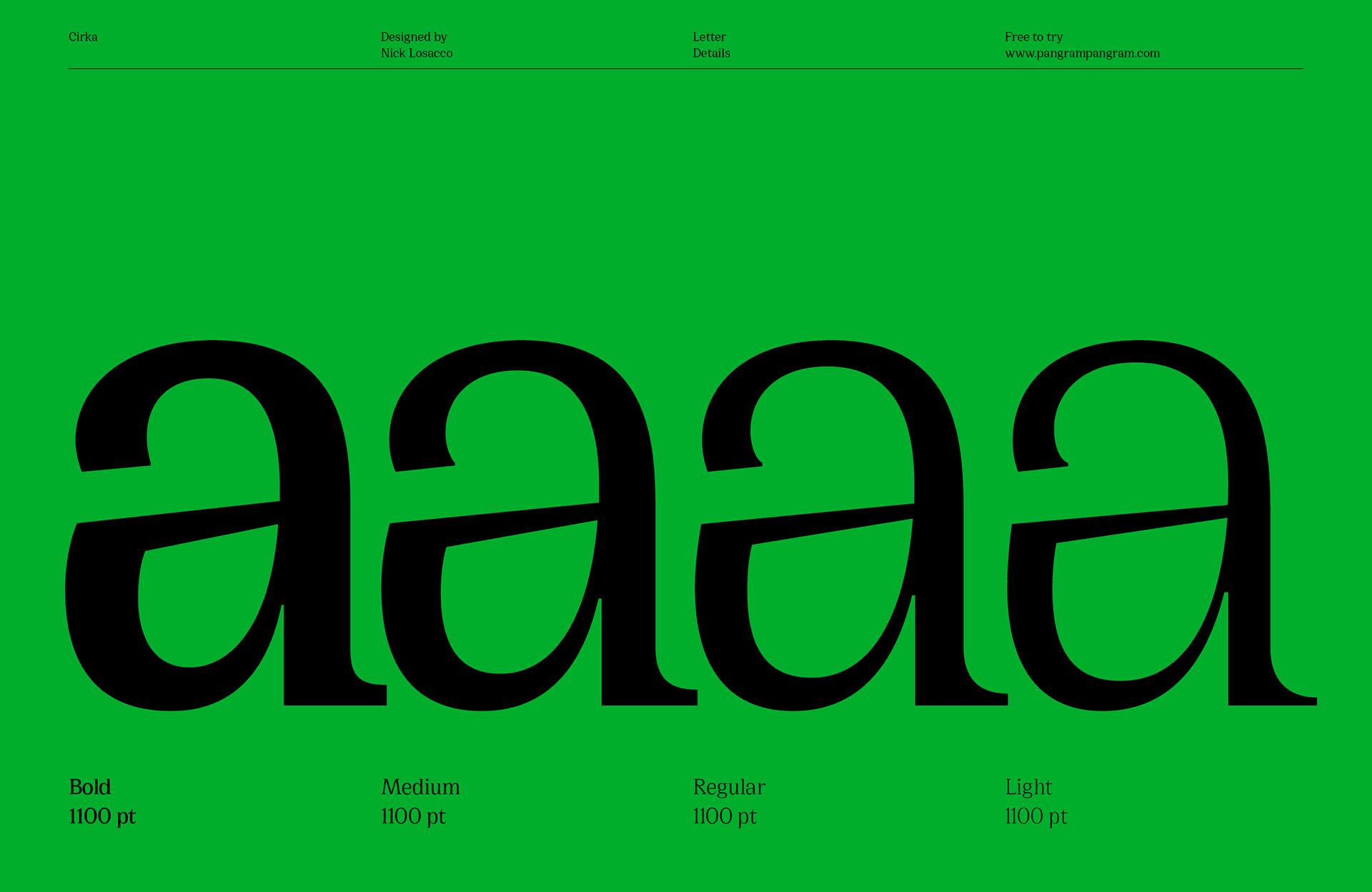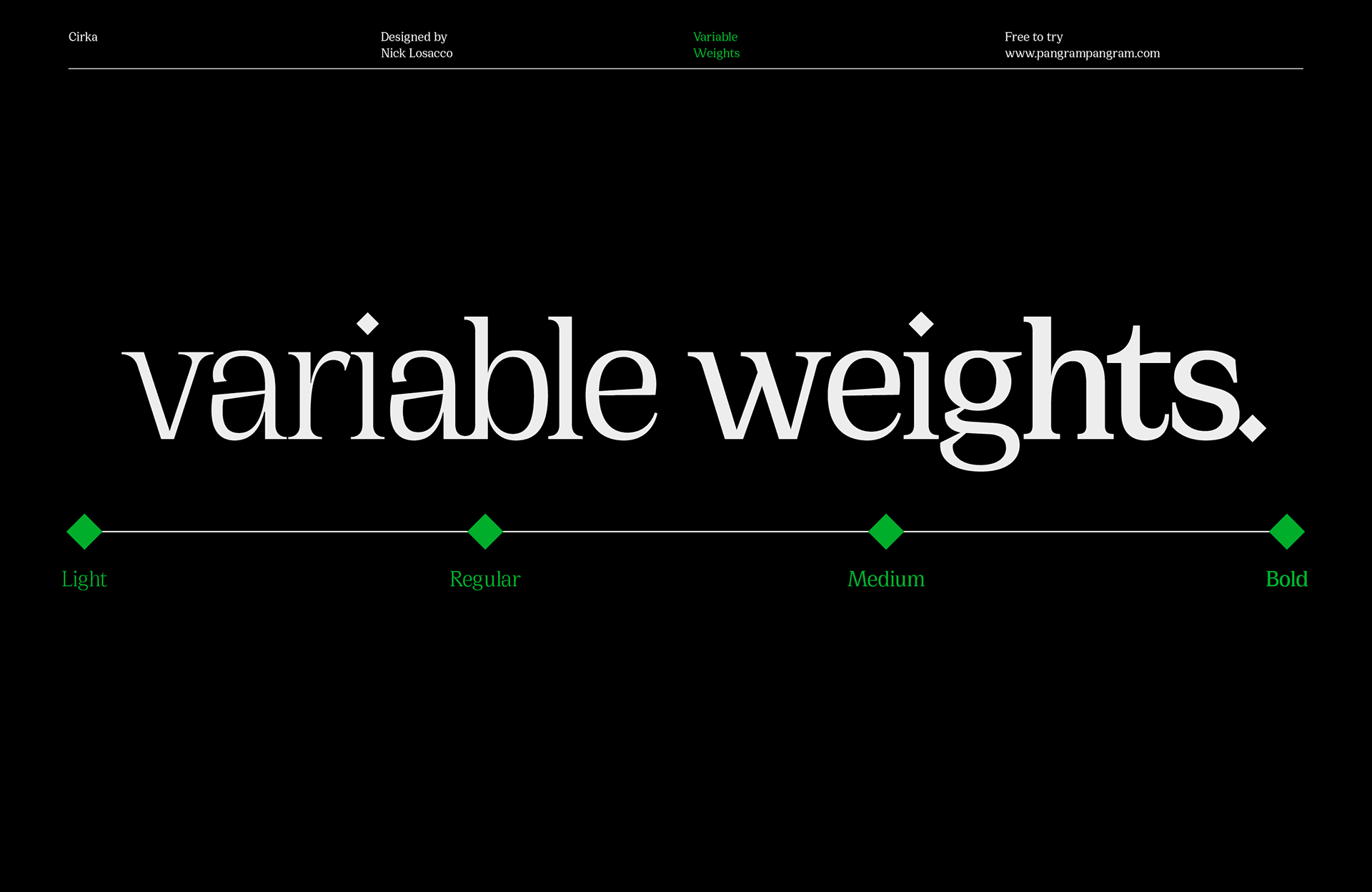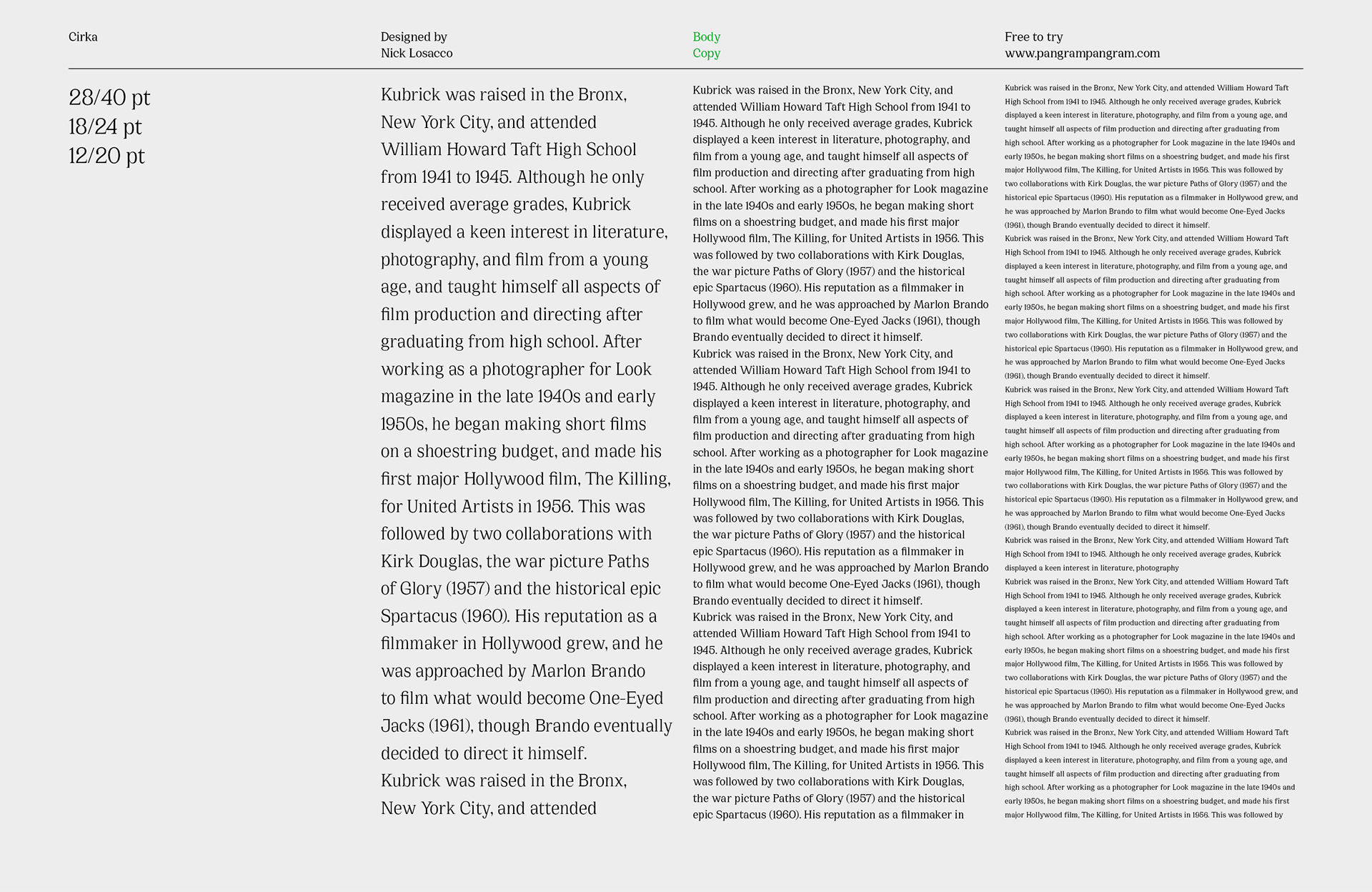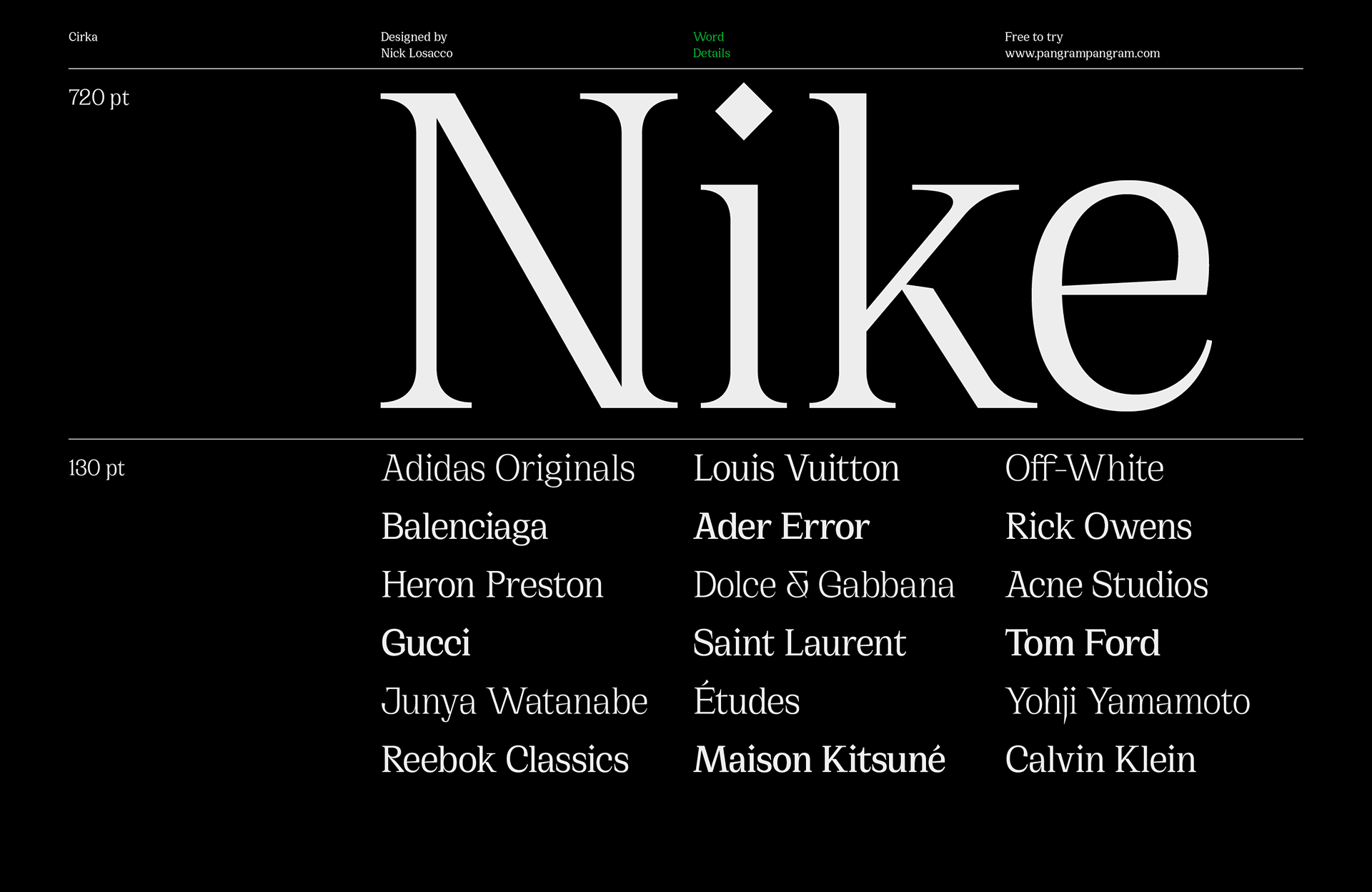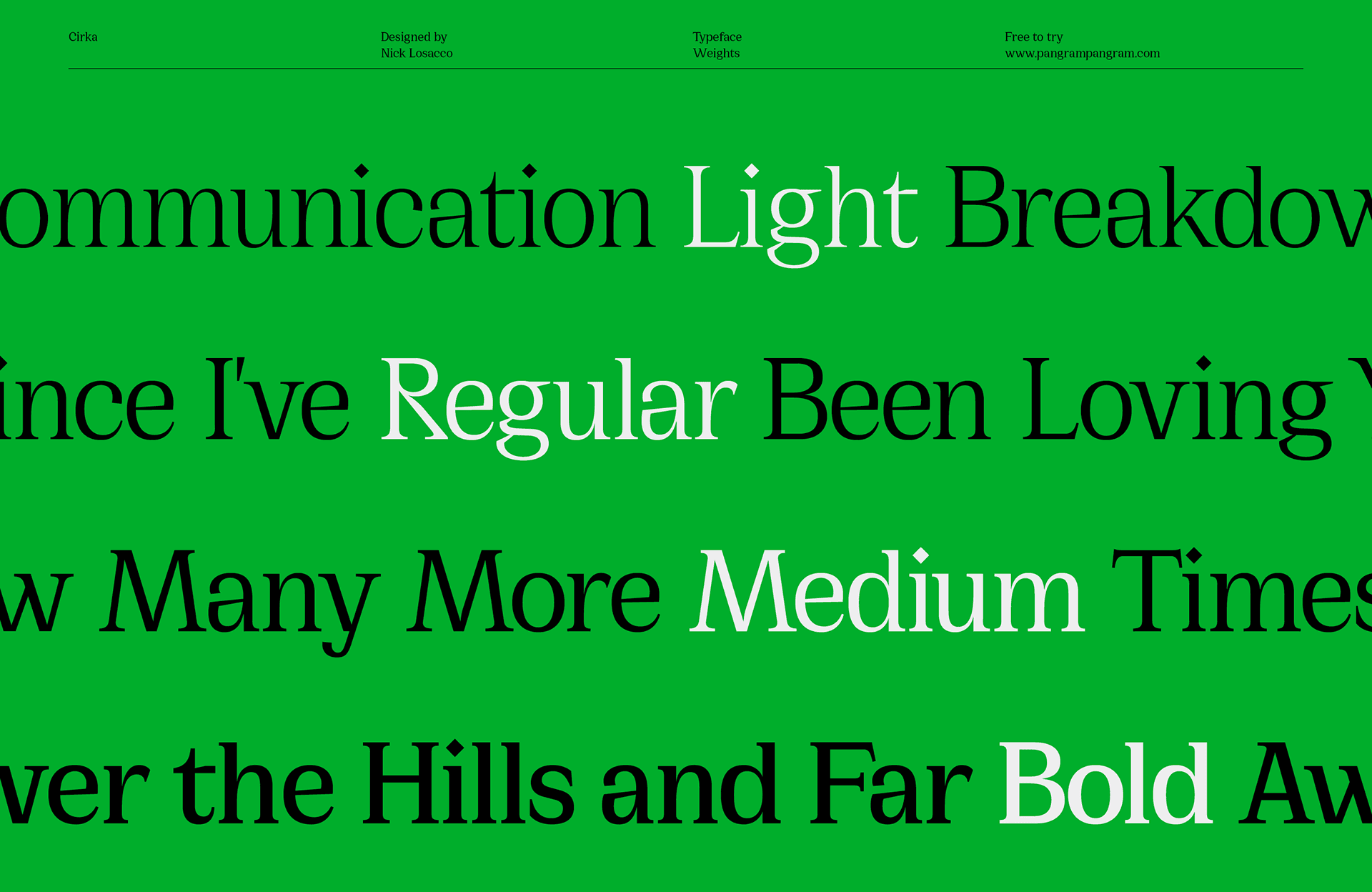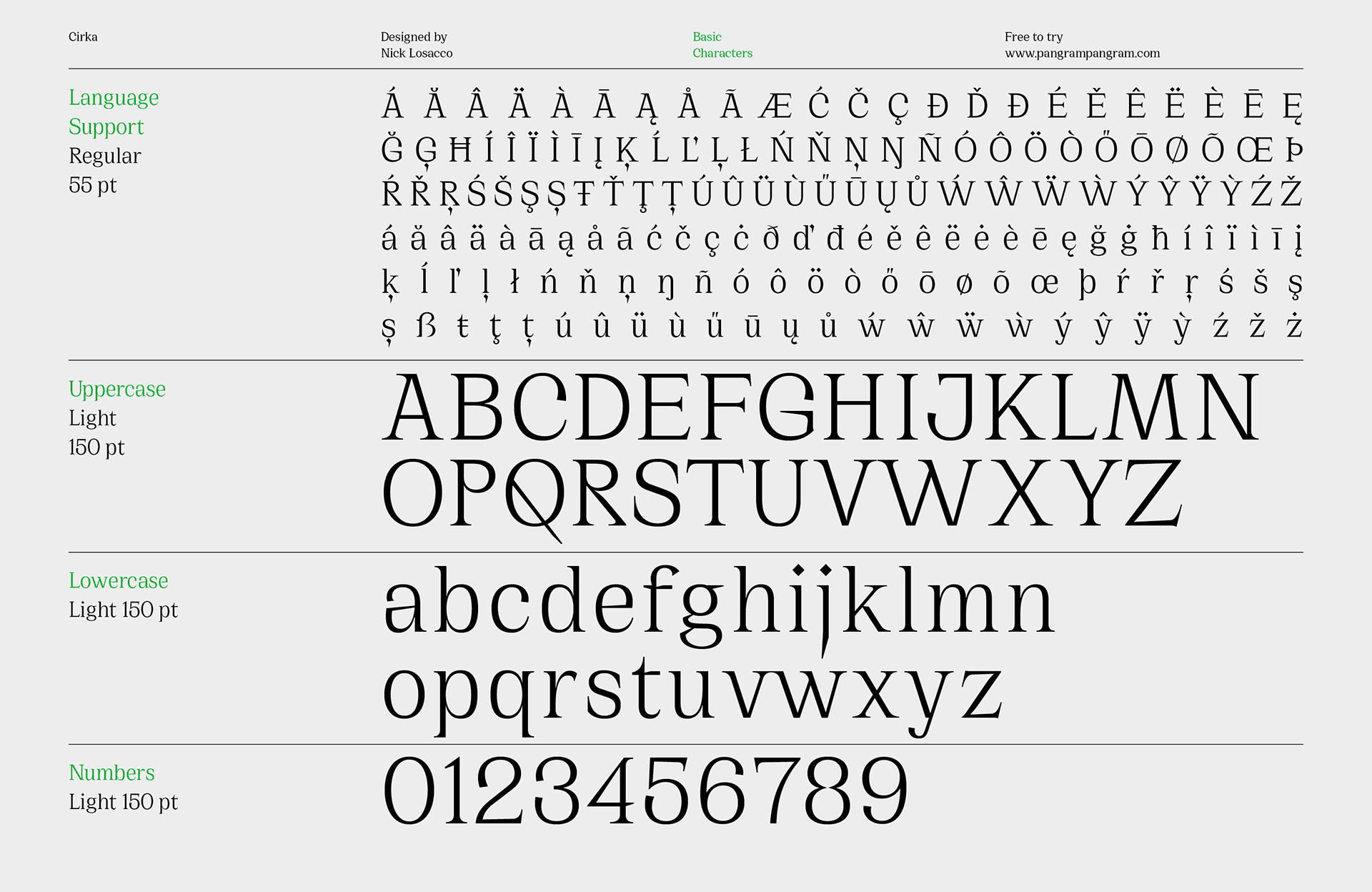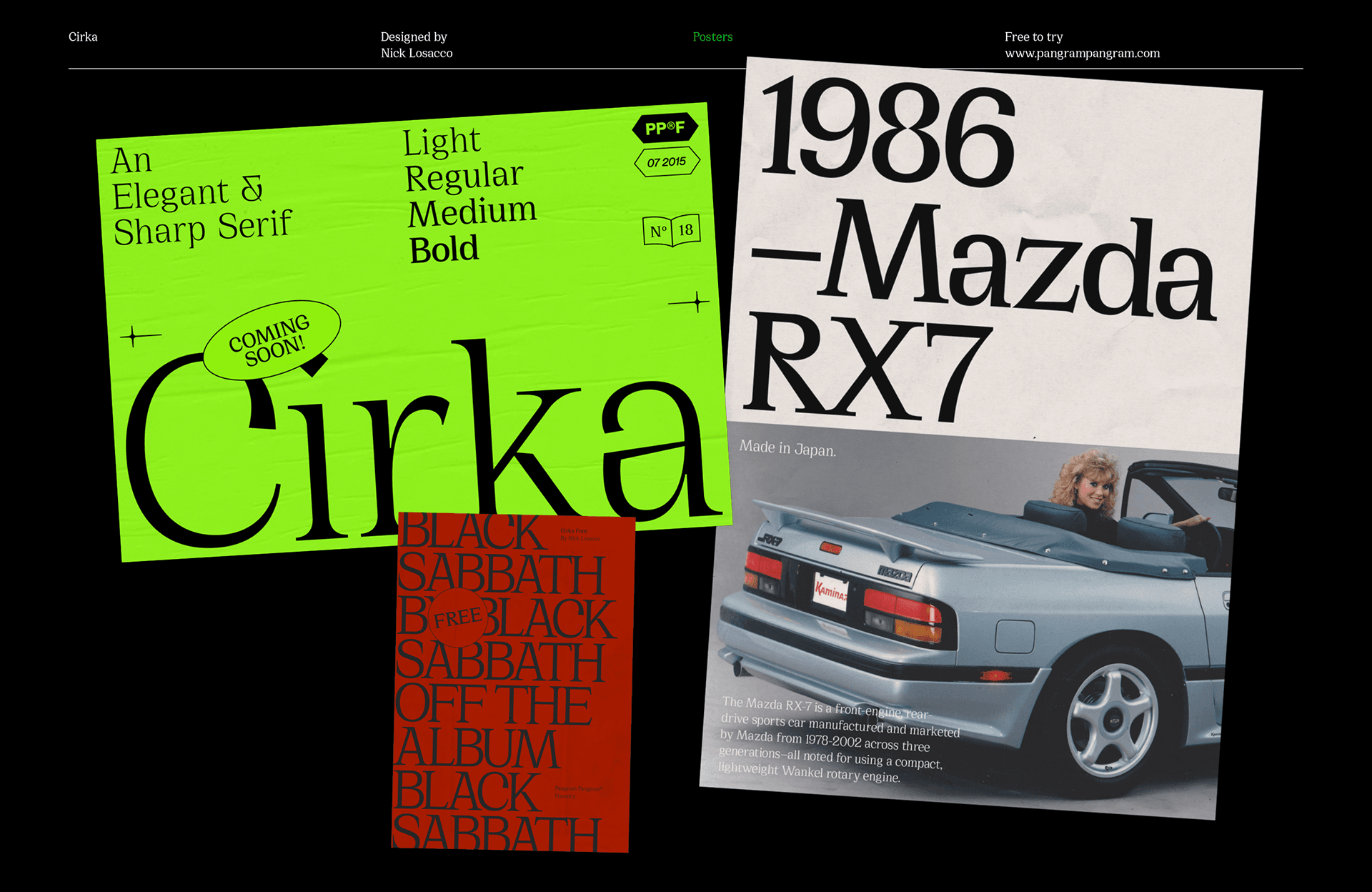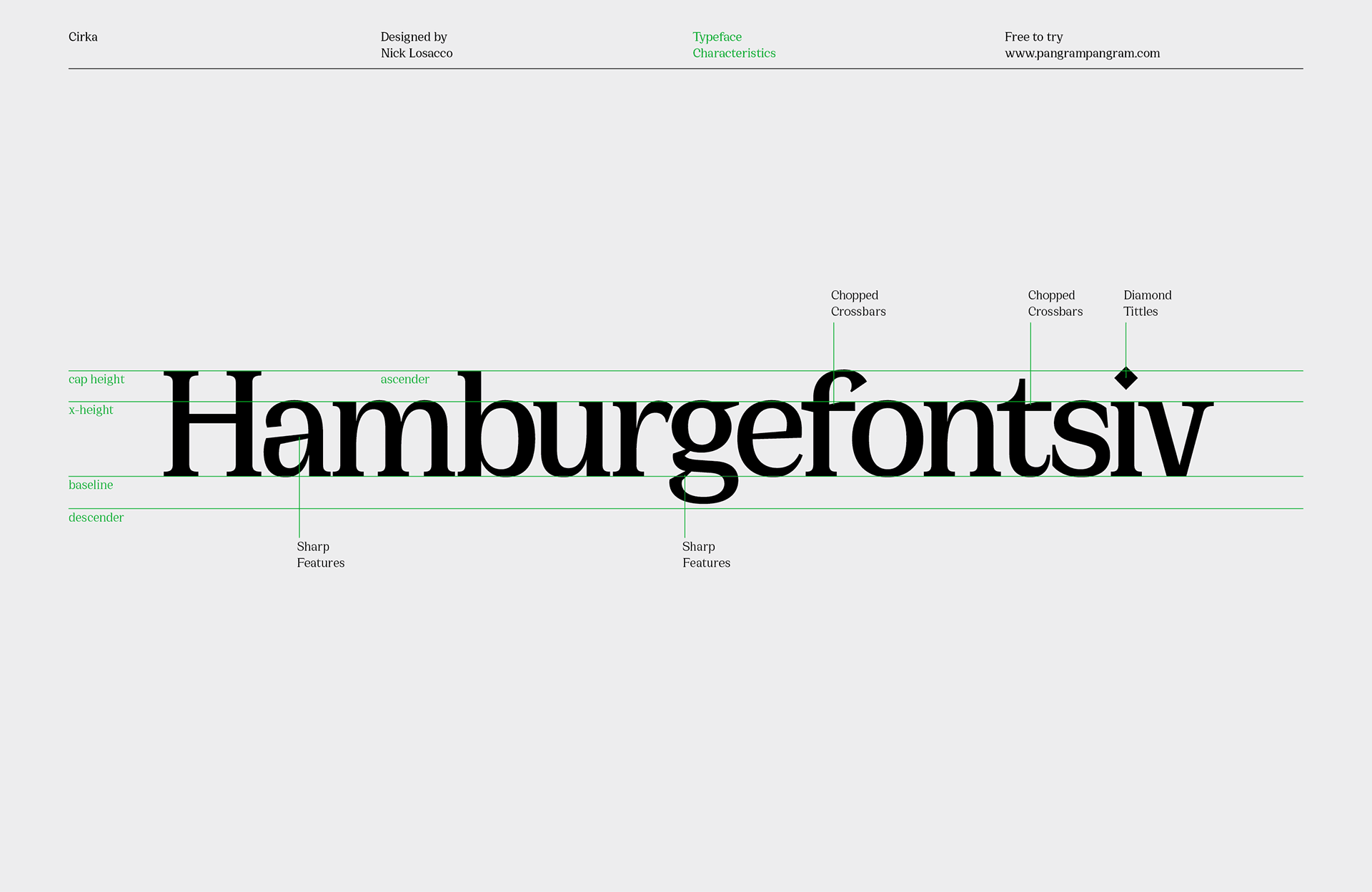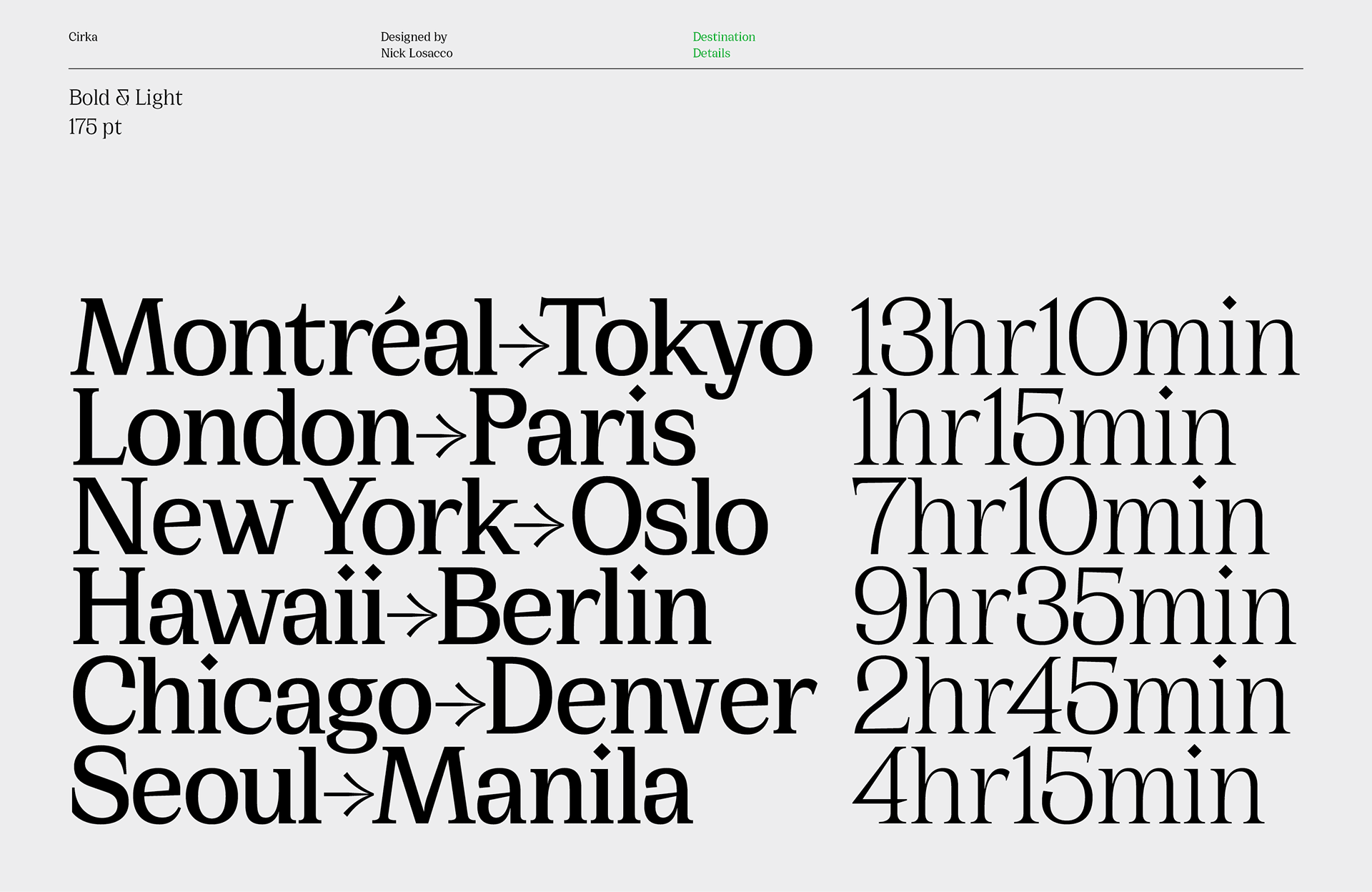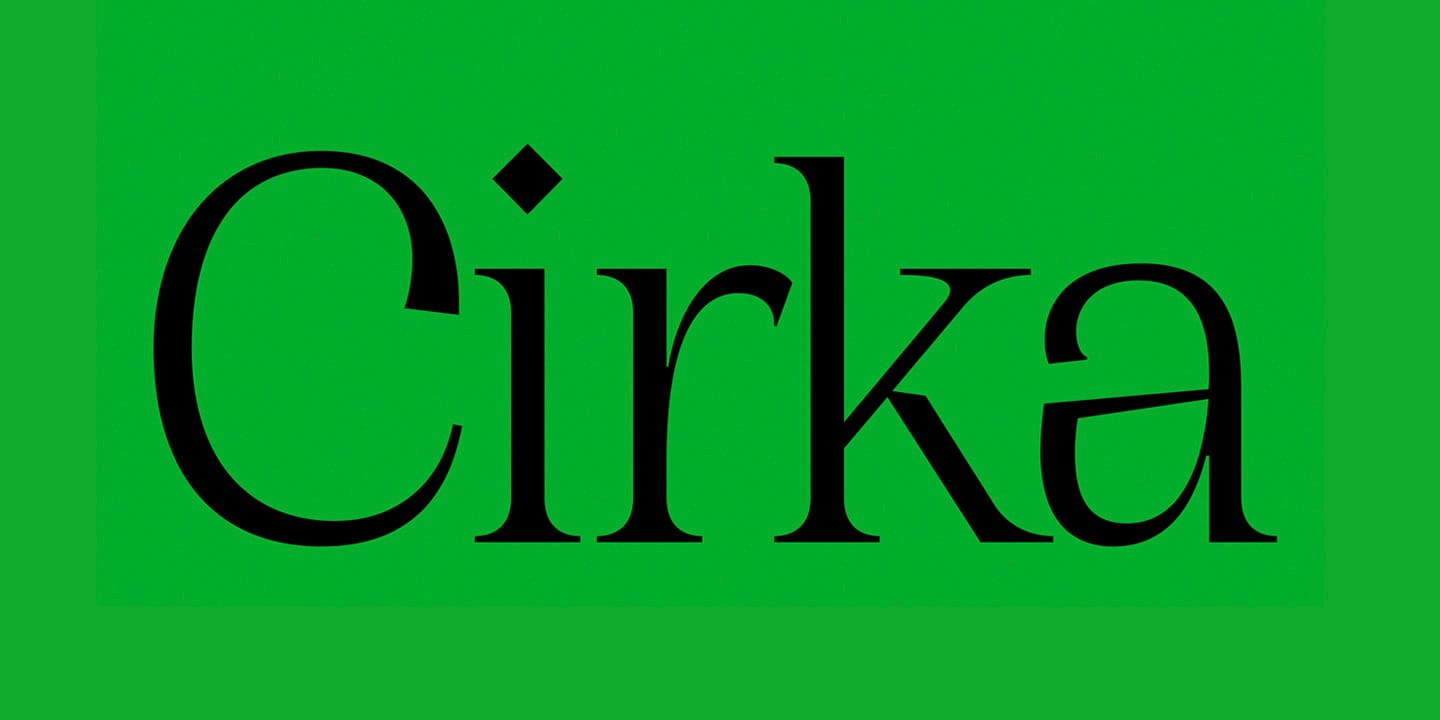
Cirka là một kiểu font chữ thanh lịch kết hợp các hình thức cổ điển và một trục thẳng đứng với các serifs nhọn, sắc nét. Nó hoạt động tuyệt vời với kích thước lớn trên áp phích hoặc tiêu đề, hoặc nhỏ, dưới dạng văn bản nội dung.
Cirka Font Family bao gồm 4 weight với 380 glyph.